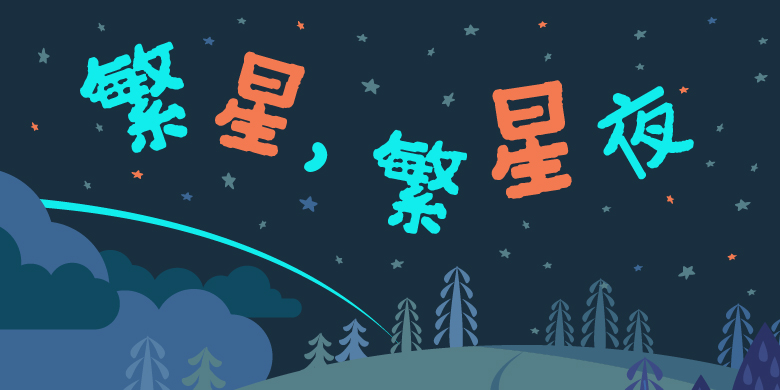
方正字汇-邻家小哥体
字体品牌: 方正字汇 设计师:尹戈 字体分类:创意书写 字体属性:精品字 字符集:大陆简体(GB2312-80) 发布时间: 2021
邻家小哥体是作者第一次尝试做字体设计,自由随意,有点幽默感,辨识度比较高,没有过于刻板的追求字的结构,就像某位邻家小哥或快递小哥写的字,适合于漫画、插图以及其他少儿产品等应用领域。